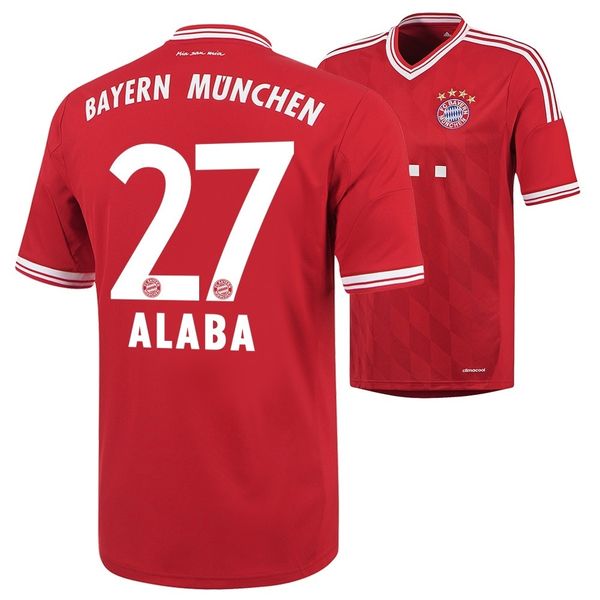
Fc bayern Trikot 2013
Stell doch mal ein Bild der Schrift ein, dann ist die Chance größer, dass Dir geholfen werden kann.
Soweit ich weiß lässt sich Bayern München die jeweilige Schrift immer speziell entwerfen (auch wenn die immer entfernt einer Standardschrift ähneln mag) und lassen dann sogar jede einzelne Ziffer als Bildmarke markenrechtlich schützen, um so gefälschte Fanartikel besser verfolgen zu können.
Die Buchstaben sehen nach einer leicht modifizierten Futura medium condensed bzw. bold condensed aus. Die Ziffern sind freilich etwas ganz anderes.